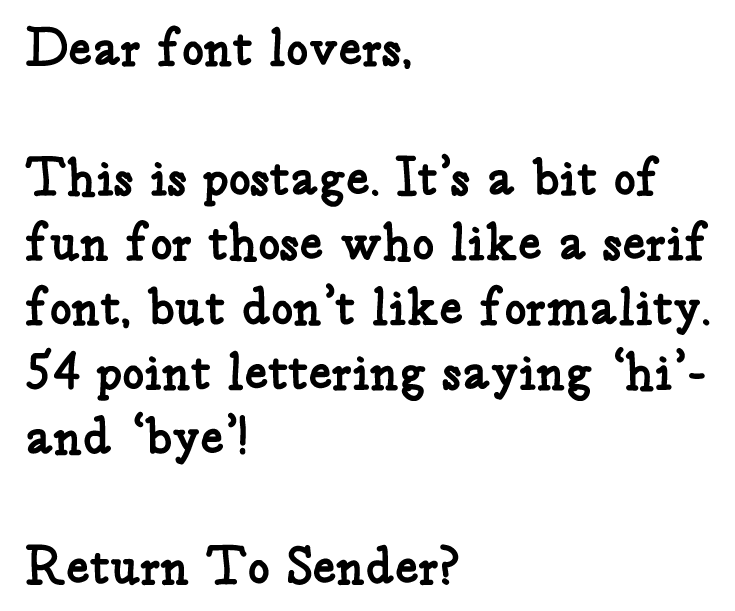
A fonte Postage oferece uma sensação amigável e alegre que é perfeita para criações online de e-mail, anúncios digitais ou qualquer outro tipo de conteúdo visual que você deseja comunicar de forma suave e envolvente. Desenvolvida pelo designer Hamilton, essa fonte Script oferece uma aparência fresca e informal, com traços leves e harmoniosos que transmitem confiabilidade e simplicidade. Com sua tipografia clara e bem equilibrada, a Postage é perfeita para as páginas de download de arquivos onde você deseja transmitir um conceito de facilidade de uso e conveniência. As letras da fonte se encaixam perfeitamente no formato de texto curto ou em listas, permitindo que você mantenha o design leve e eficaz necessário para a experiência online atual. Para aqueles que procuram uma fonte que combine elegância com funcionalidade, a Postage é um ótimo investimento. Seja para uma página de download ou qualquer outro tipo de material digital destinado à mobilização do público online, certifique-se de usar essa fonte para proporcionar um touch visual suave e envolvente.